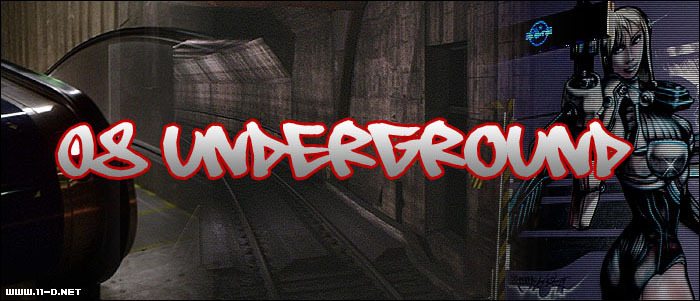
08 Underground to odważny krój pisma inspirowany graffiti, który emanuje surową, miejską estetyką. Nieregularne, odręczne pociągnięcia i postarzany wygląd nadają mu poczucie autentyczności, dzięki czemu jest to doskonały wybór do brandingu, opakowań i innych projektów designerskich, które wymagają ulicznego, undergroundowego sznytu. Solidna konstrukcja i wyrazisty charakter sprawiają, że świetnie sprawdza się w nagłówkach, logotypach i tekstach przyciągających uwagę, a wszechstronność kroju pozwala również na efektywne wykorzystanie go w tekście głównym i mniejszych formatach.
Uderzający efekt wizualny i wszechstronność sprawiają, że 08 Underground to przekonująca opcja dla projektantów, którzy chcą uzyskać odważną i mocną typograficzną obecność.